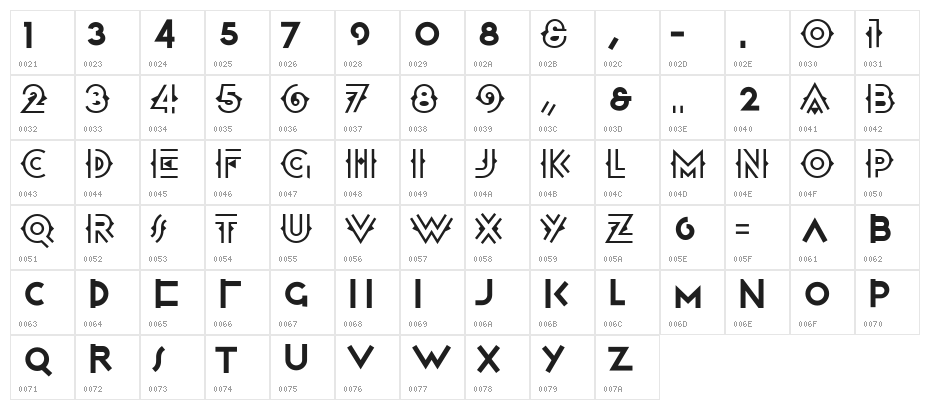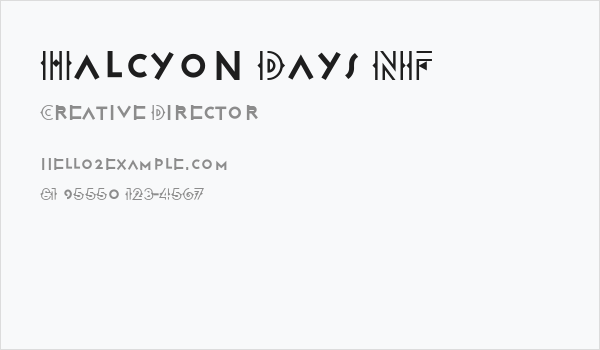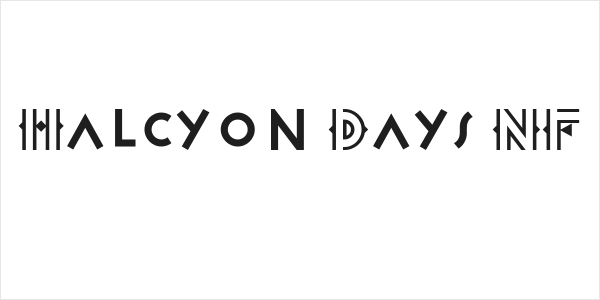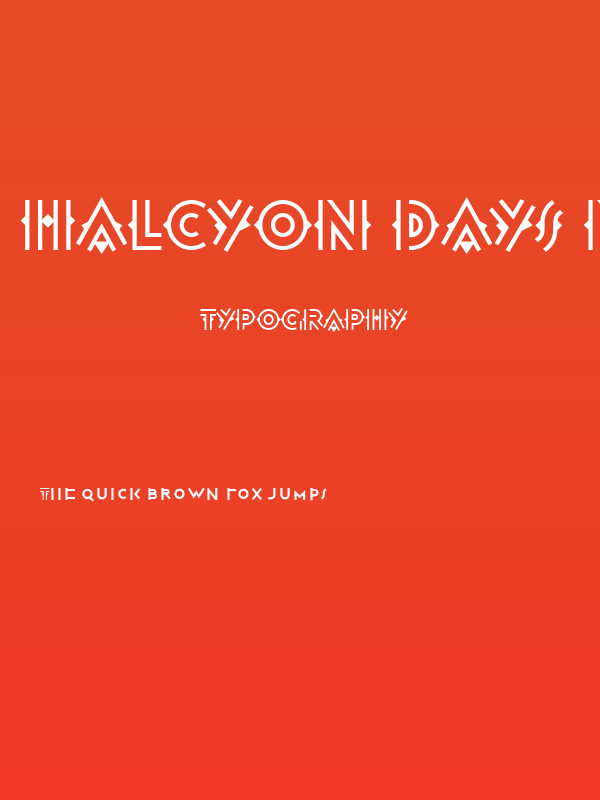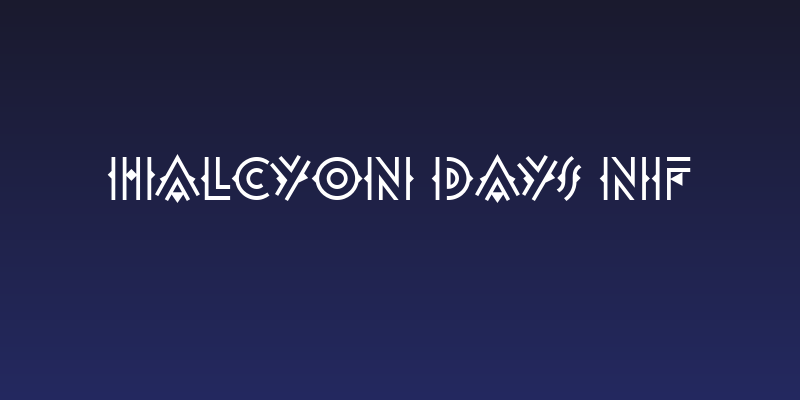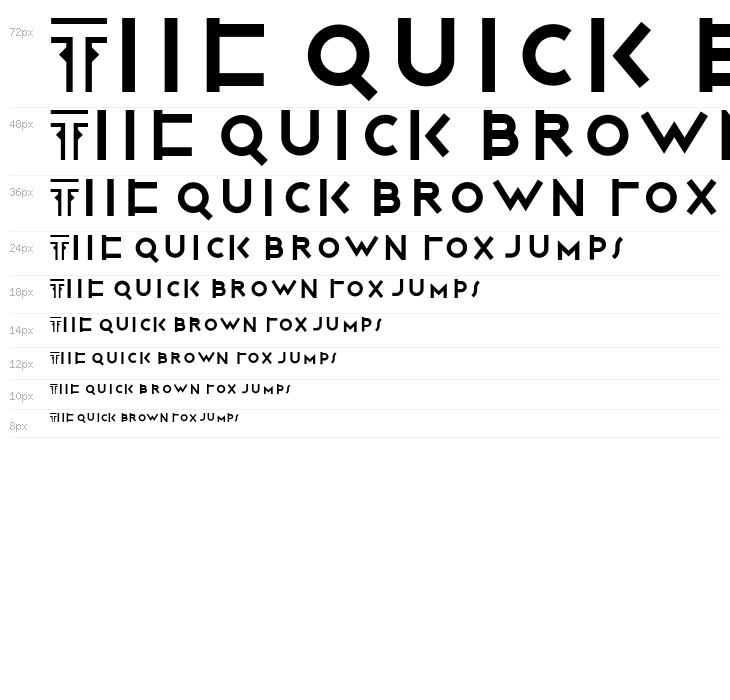
Halcyon Days NF Font
| Gesamtstil | Modern, Art Deco |
| Vorgeschlagene Projekte | Ideal for branding, posters, and headlines that require a modern and artistic touch. |